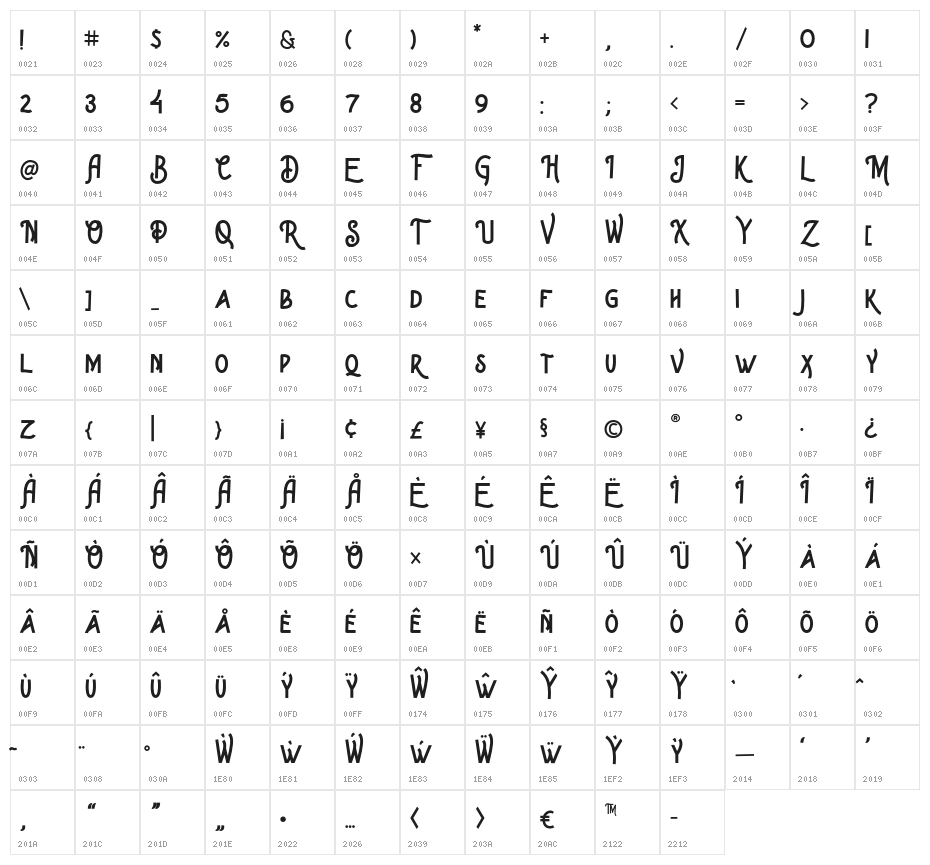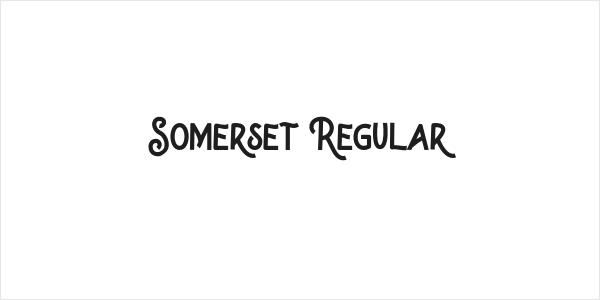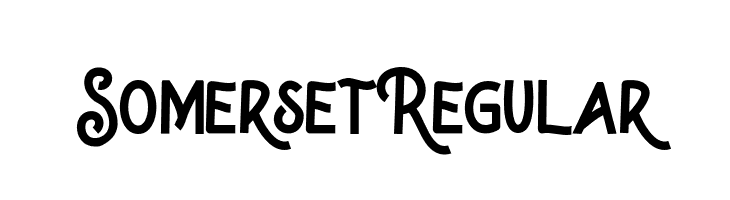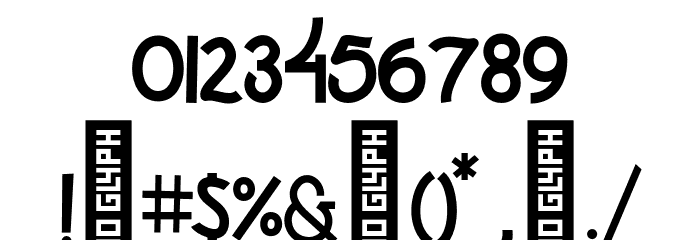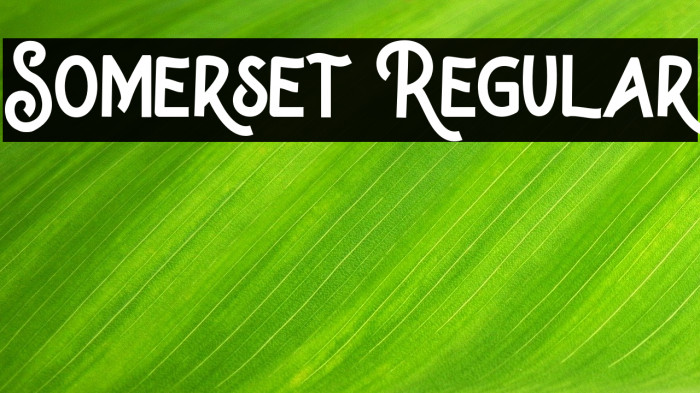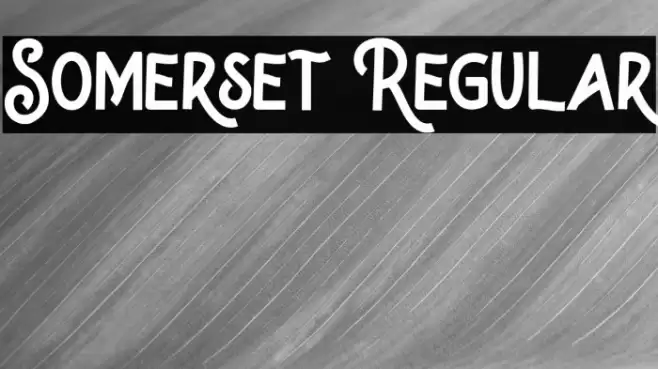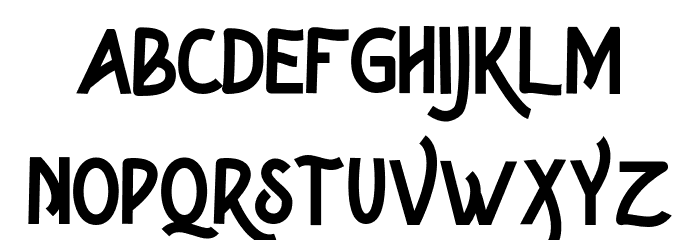
Somerset Regular Font
✎ Decorative
| समग्र शैली | Decorative |
| उपयोग का मामला | Logos, Headlines, Posters |
| सुझाए गए प्रोजेक्ट | Ideal for children's books, playful branding, party invitations, and creative posters. |